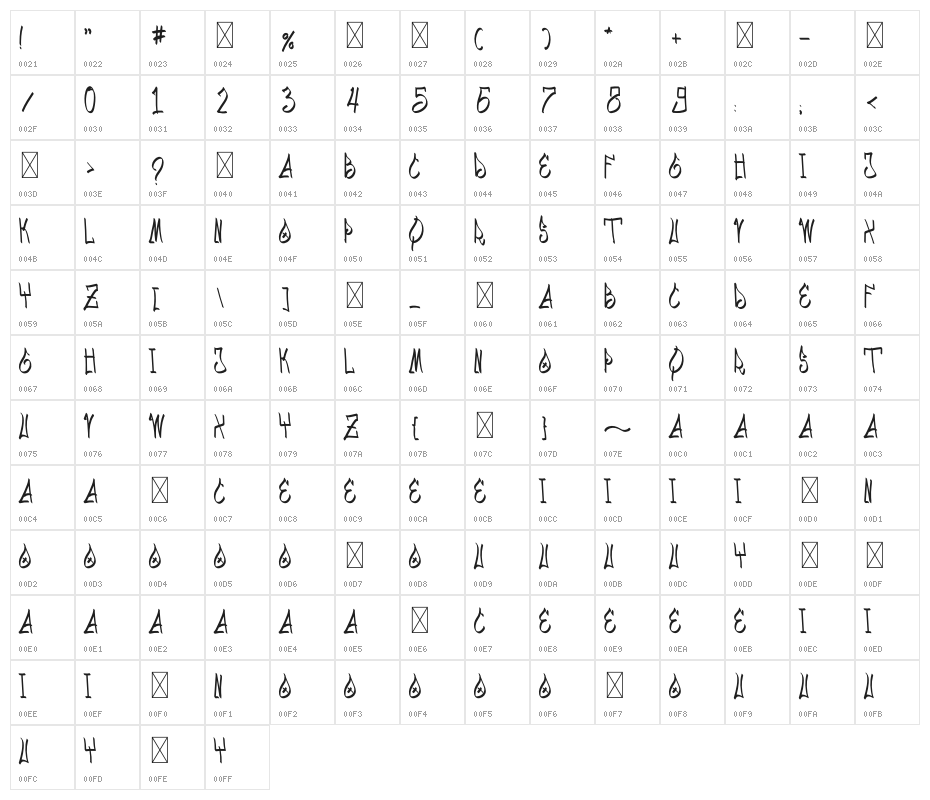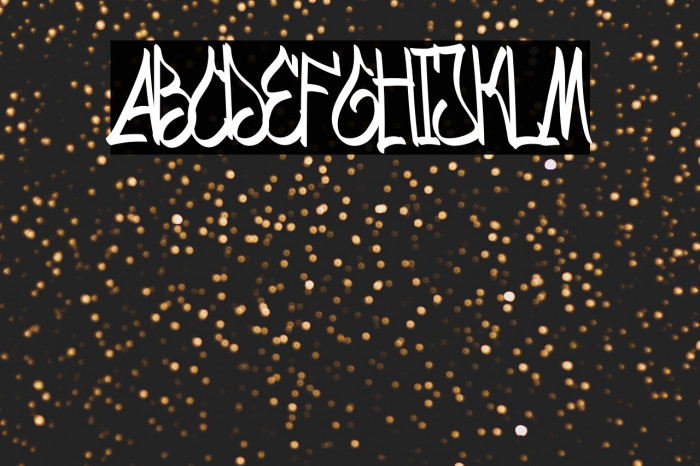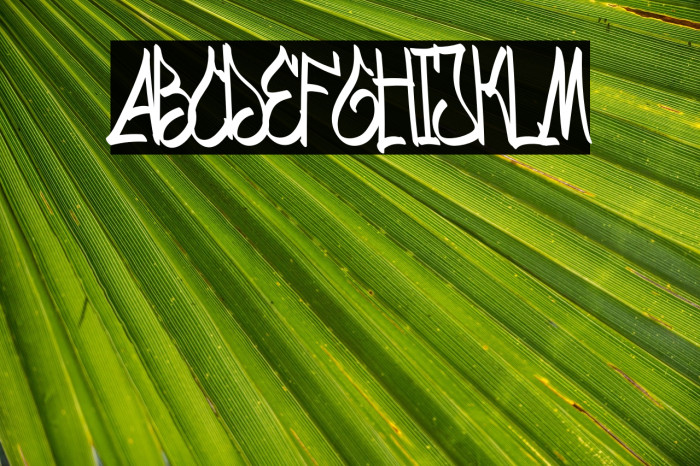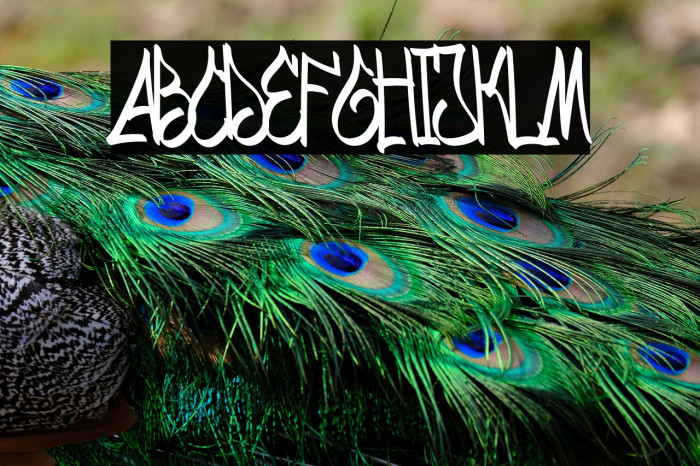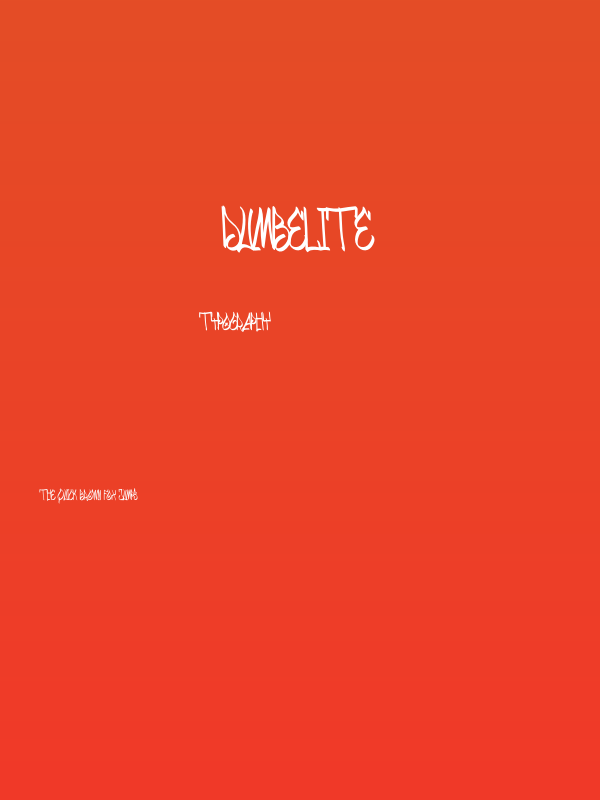
DUMBELITE Font
✎ Graffiti
| Stile generale | Modern, Urban, Graffiti |
| Caso d'uso | Logos, Posters, Headlines |
| Progetti proposti | Ideal for street art designs, music album covers, urban-themed posters, and edgy branding projects. |